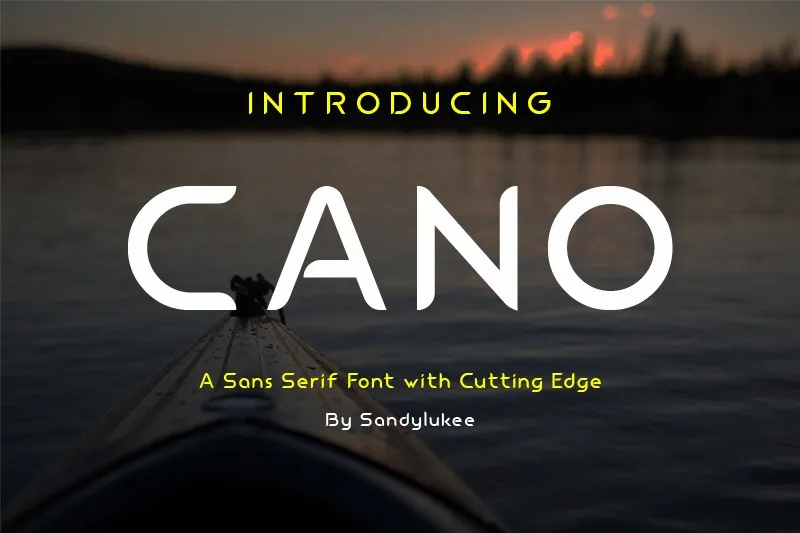
Cano Sans Serif Font – Fonte Grátis
Cano Sans Serif Font
Esta é uma fonte sans-serif que oferece detalhes aparentemente limitados para uma fonte simplificada e moderna. Ela é perfeitamente adequada para os requisitos de marca, logos e temas tecnológicos. A sua simplicidade faz com que seja muito fácil de usar. É compatível com qualquer software gráfico como o Adobe Illustrator, Photoshop ou até mesmo Microsoft Office. A fonte Cano Sans Serif é um excelente complemento para qualquer projeto digital, tornando-se uma opção clara e moderna que se encaixa em várias necessidades, não importa a complexidade do seu design. A sua facilidade de utilização e capacidade de ser instalada num grande número de software de edição gráfica tornam-na um ativo valioso para designers e criativos.